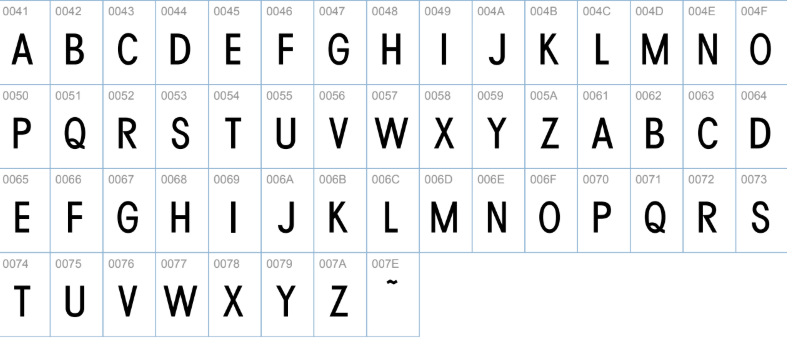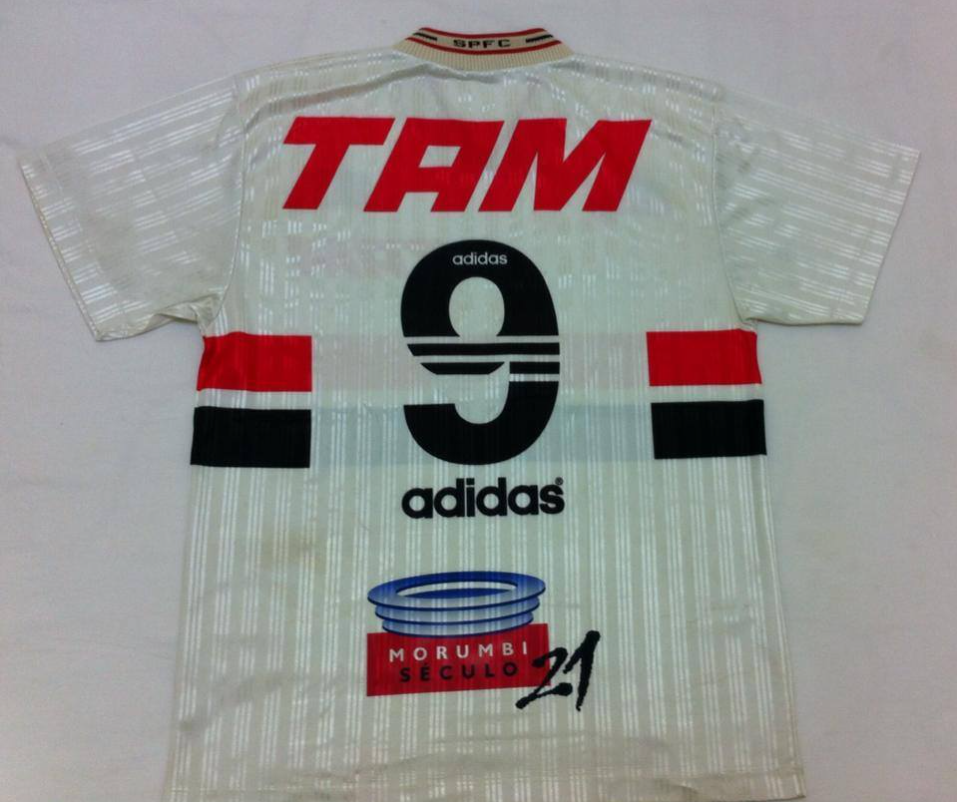
Para os fãs de design esportivo e para a torcida apaixonada do São Paulo FC, o final dos anos 90 evoca uma nostalgia imediata. Foi uma era marcada por uniformes icônicos fornecidos pela Adidas, que vestiu o Tricolor em momentos memoráveis. A tipografia utilizada nas camisas entre 1996 e 1999 é um desses detalhes inesquecíveis, sinônimo de um período de ídolos e conquistas.
O Estilo Visual: Força e Tradição dos Anos 90
A tipografia da Adidas para o São Paulo nesse período é marcada pela robustez. É uma fonte “blocky” (em bloco), com peso e excelente legibilidade, desenhada para se destacar no campo. Seus cantos são sólidos, mas com uma leve suavização que a torna única. Ela transmite a força e a seriedade do clube, sendo instantaneamente reconhecível nas costas de camisas usadas por lendas como Rogério Ceni (em seus primeiros anos como titular), Denilson e França, notavelmente na campanha vitoriosa do Campeonato Paulista de 1998.